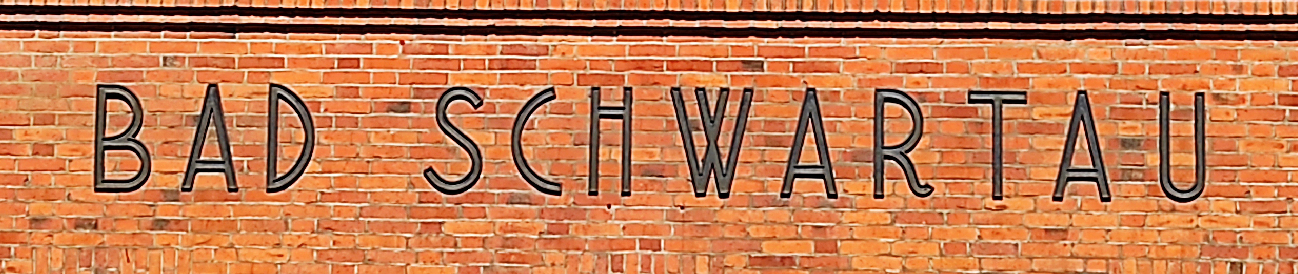
Schrift am Stellwerk "Sn" in Bad Schwartau
ich möchte die Schrift an unserem Stellwerk in Bad Schwartau für einen Modellbau nachbauen. Aber im CAD die Konturen nachmalen ist äußerst schwierig, da der Blick verzerrt ist.
Aber vielleicht kann mir jemand weiterhelfen. Wenn es geringfügige Abweichungen gibt, dann kann ich damit leben. Es kann durchaus sein, dass die Schrift gestaucht am Gebäude steht.
Hier ein Bild:
Genau die gesuchte wirst du vermutlich nicht finden, da solche Beschriftungen früher Werke von Schildermalern waren, die sich zwar Inspirationen geholt, aber idR frei gestaltet haben.
Ähnlich:
das ist doch fast passend. Muss ich das "W" nur noch etwas nachbearbeiten.
Aber das sollte nicht das Problem werden, weil ich versuche die Schrift in AutoCAD einzubinden und dann in seine Konturen zerlege.